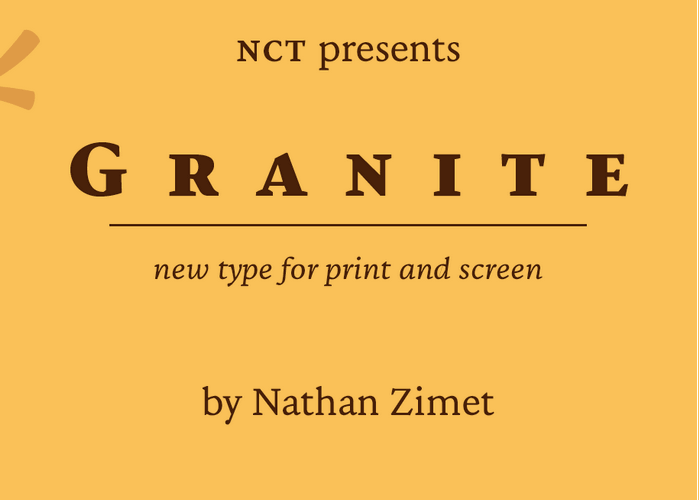
Descubra a NCT Granite Font Family para suas necessidades de design. Introduzida pelo designer Hamilton, essa serif está revivendo as formas do tipo renascentista na era moderna. Através de uma tipografia robusta e funcional, esta fonte é projetada tanto para uso em tela quanto impressão. Com o itálico praticamente da mesma largura que a versão romana, você pode ler facilmente textos longos sem esforço. Esta família de tipo serif certamente atenderá às suas necessidades de design, trazendo um toque de elegância e funcionalidade à sua obra. Seja para projetos impressos ou digitais, NCT Granite é uma escolha segura que valoriza a legibilidade e a estética contemporânea.